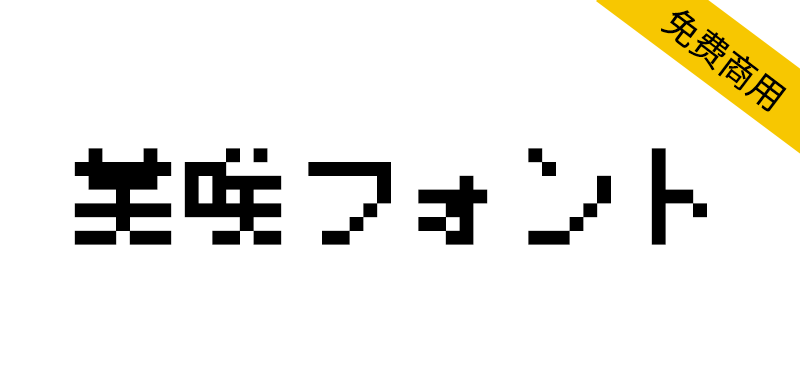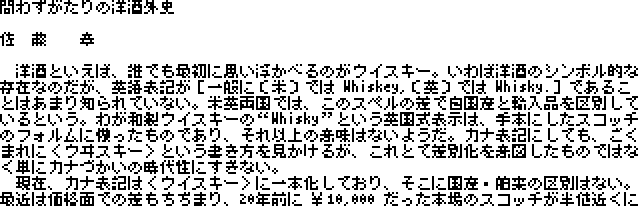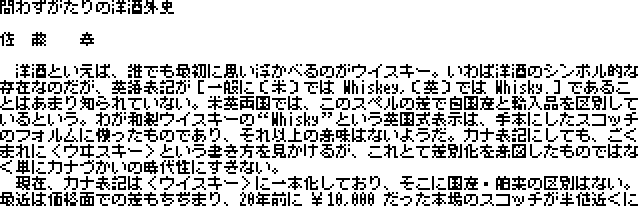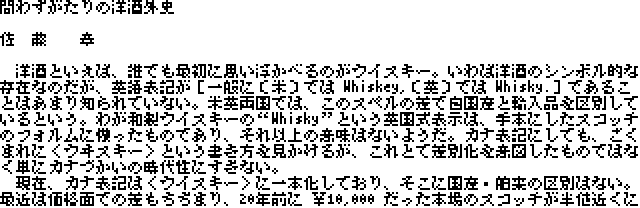
【美咲8×8点阵体 美咲フォント】一种 8×8 点的日语像素字体
美咲8×8点阵体(美咲フォント)是一种 8×8 点的日语像素字体。支持JIS 1级和2级。除某些符号外,所有字符都在 7 x 7 点的范围内,因此即使字符彼此相邻,也可以确保行距和字符间距。
美咲ゴシック (倍角画像)
美咲ゴシック第2 (倍角画像)
美咲明朝 (倍角画像)